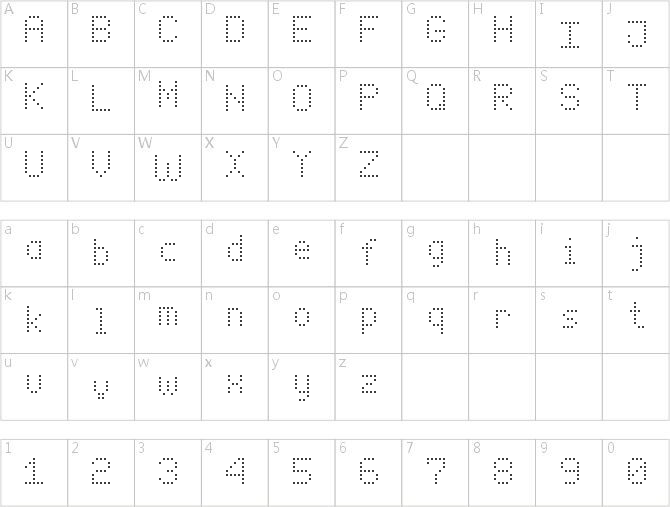
Enhanced-Dot-Digital-7
Enhanced-Dot-Digital-7介绍
Enhanced-Dot-Digital-7字体字库是一款让人赏心悦目、百看不厌的英文字体,适合各类广告和产品包装设计应用,字体大小0.06MB,格式为ttf字体,上传用户是那是不变的,作者/版权方为未知